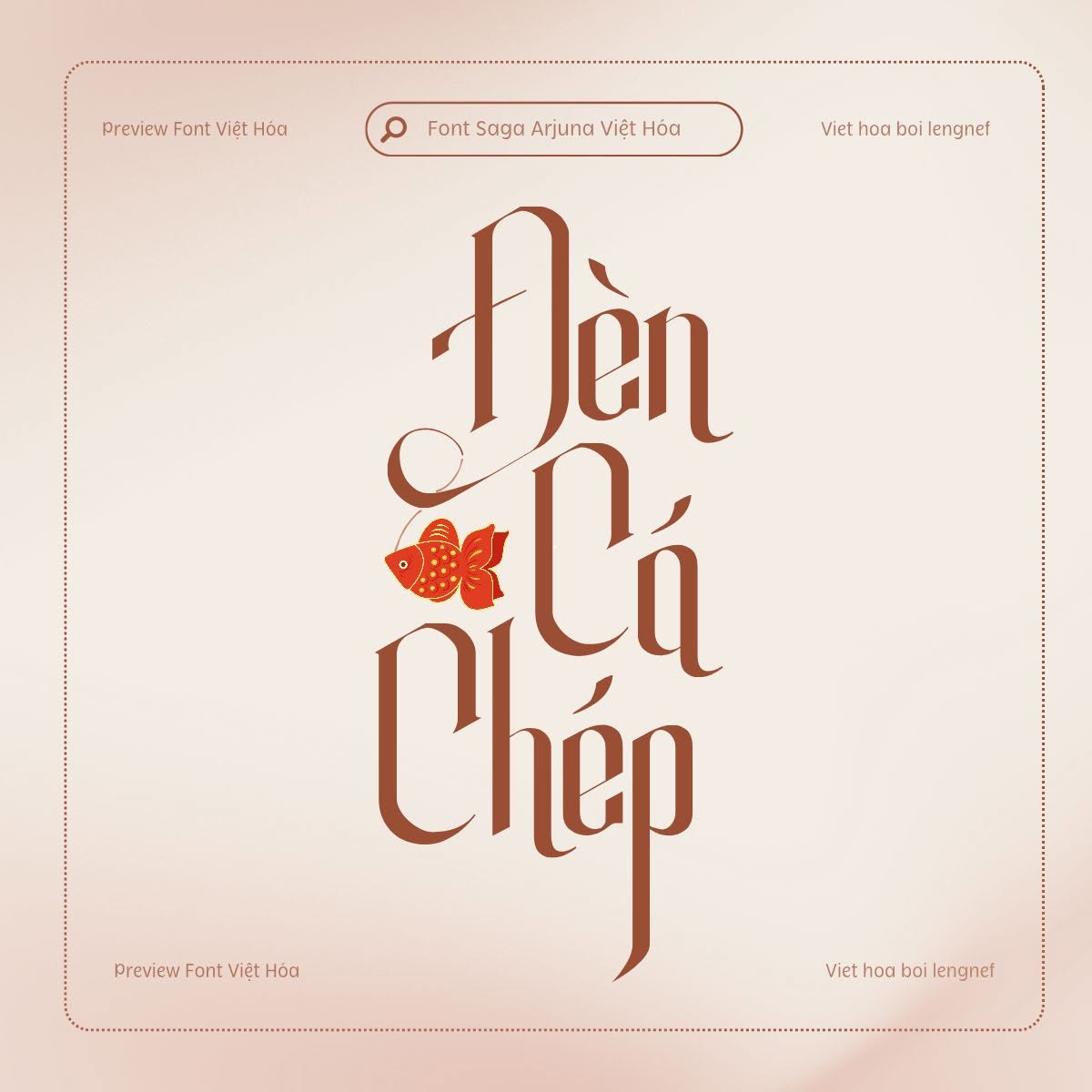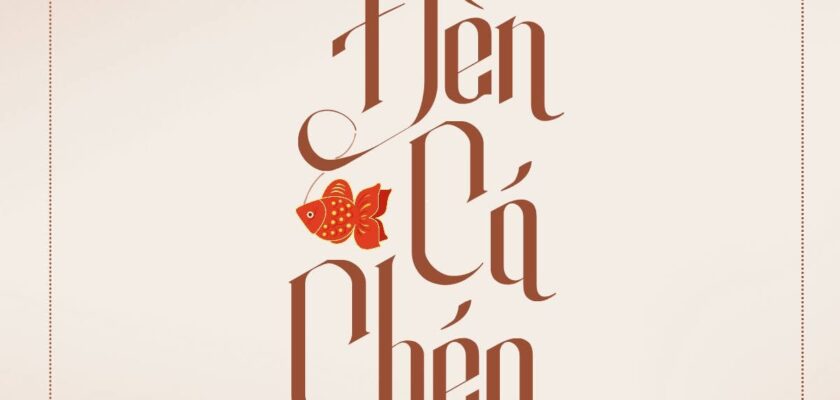
- Tác giả: Saxofont
- Việt hóa: lengnef
Saga Arjuna là một phông chữ hiện đại, thanh lịch và sang trọng, kèm các ký tự thay thế tùy chỉnh. Kiểu chữ bút ngòi dẹt cùng các ký tự nét đậm mỏng khác nhau rất phù hợp để thiết kế logo và tiêu đề, cũng như lý tưởng cho bìa sách, bao bì sản phẩm, quảng cáo, xây dựng thương hiệu,…